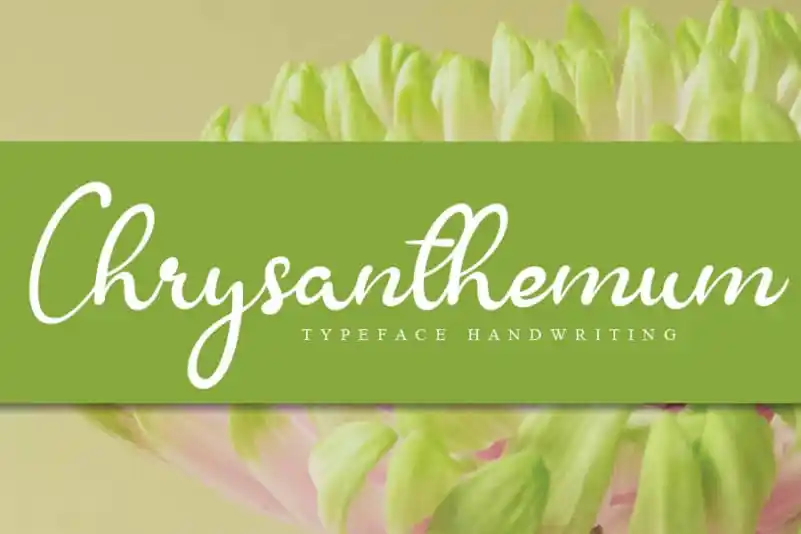
Chrysanthemum Handwritten Font – Fonte Grátis
Chrysanthemum Handwritten Font
A Chrysanthemum Font é uma elegante e delicada caligrafia manuscrita que traz beleza ao seu design. Sua composição bem equilibrada faz dela um recurso versátil para uma ampla variedade de criações gráficas. Uma vez adicionada a seus projetos mais criativos, ela se destaca e transforma suas ideias em algo realmente vivo e imersivo. Essa fonte manuscrita oferece uma textura suave e um estilo fluido que combina perfeitamente com diversos estilos de design. Seja para criar gráficos digitais, letras impressas ou até mesmo desenhos a mão livre, ela se adaptará maravilhosamente. A Chrysanthemum Font é a escolha ideal para designers buscando uma fonte que não apenas complementa seu trabalho, mas também o potencializa, transformando suas ideias em obras vivas e inspiradoras.